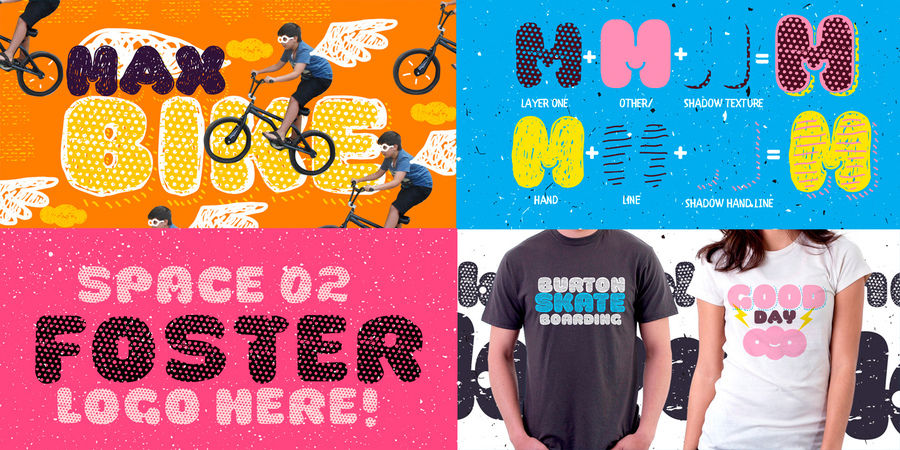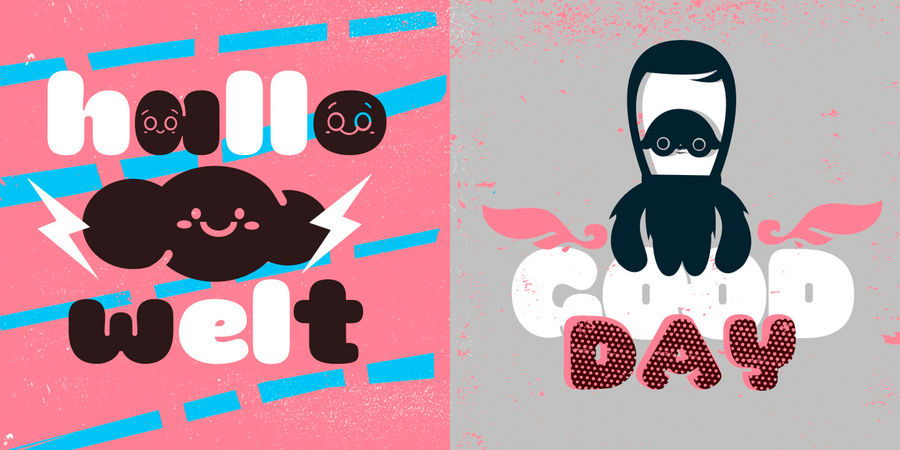
La Mona Pro це редизайн шрифту Mona 2012 року. Це багатошарове суперсімейство підтримує безліч мов, в тому числі грецьку абетку та кирилицю. La Mona Pro містить лігатури, орнаменти, тіні, розчерки й альтернативи (72 накреслення) Грайтеся! :)
Шрифт розробив Родріго Арая Салас у 2016 році.
реклама, плакат, журнал, мультфільм, комікс, листівка, вивіска, етикетка, пакування, обкладинка, анімація, стінгазета, відео, стікер, наліпка, альбом, шкільна дошка, афіша, привітання, меню Адаптованість гарнітури до носіїв:
Асоціації з сімейством шрифтів La Mona ProОсобистість і характер гарнітури:
веселий, пузатий, задерикуватий, смішний, доброзичливий, добродушний, добрий, радісний, грайливий, привітний, пустотливий, оригінальний, свіжий, стиглий, соковитий, смачний, важкий, помітний, яскравий, дитячий, наївний, карикатурний, милий, мультяшний, дотепний, домашній, літній, М'який, щедрий, пишний, затишний, приємний, живий, гладенький, святковий, тісний, товстий, прикольний, няшний, усміхнений, апетитний, солодкий, щасливий, зимовий, творчий, чорний, фруктовий, ягідний, рясний, насичений, пухкий, спекотний, крафтовий, артізанальний, вернакулярний, ручний, рукотворний, блискучий, глянцевий, прозорий, ніжний, неохайний, недбалий, ажурний, пухнастий, ремісничий, кольоровий, характерний, виразний, потішний, гулящий, зелений, кустарний, саморобний, нерівний, грубий, прямокутний, примітивний
молоко, булочка, десерт, солодощі, кондитерська, випічка, булочна, м'яка іграшка, дитяча книжка, фарби, фарба, гумор, анімація, іграшка, дитяче харчування, їжа, закуска, зоопарк, клоун, розфарбування, гра, фаст фуд, пончик, зоомагазин, тварини, відпочинок, цирк, мультфільм, дитсадок, дитячий ранок, сік, канікули, торт, цукерки, крем, згущене молоко, варення, подарунки, свято, день народження, школа, табір, шоу, телебачення, соус, сметана, кетчуп, жуйка, підгузок, фрукти, мармелад, розваги, сир, графіка, ілюстрація, дім, ранок, спальня, подушка, родина, малюк, собачка, котики, смузі, учень, школяр, школярка, льодяник, чіпси, Christmas, море, АСМР, кролик, Хюґе, вечірка, тусовка, реклама, хенд мейд, дача, фестиваль, ярмарок, базар Гарнітура має ознаки стилів: